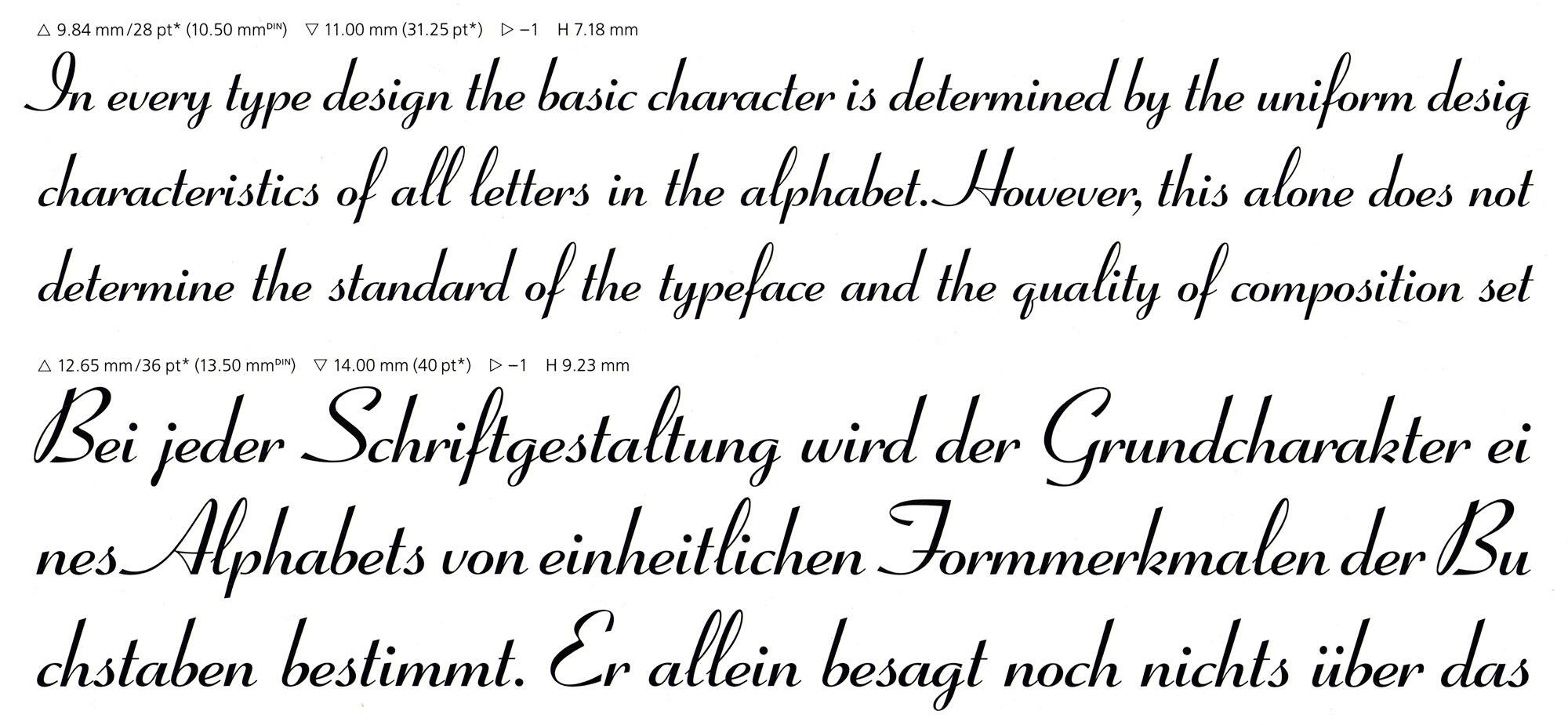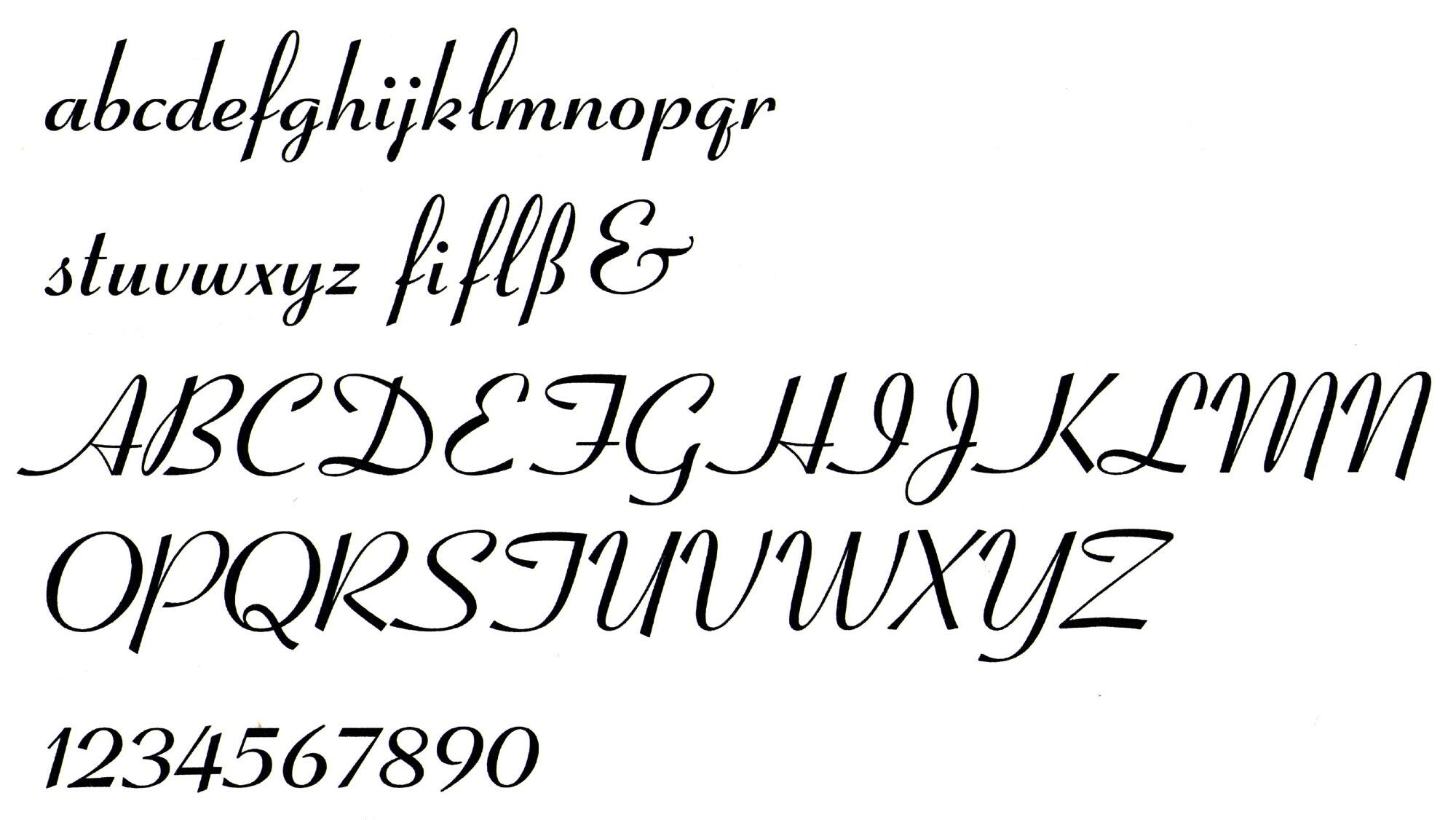
Die Coronet ist eine Schreibschrift in zwei Strichstärken von Robert Hunter Middleton und erschien in den 1930er-Jahren zunächst für das Ludlow-System. In der Folge entstanden aber auch zahlreiche Adaptionen für den Foto- und Digitalsatz. Die Schrift ist heute in ein oder zwei Schnitten über URW, ITC, Ascender (als Crestwood), Red Rooster, Bitstream und Tilde (als Ribbon 131) erhältlich.